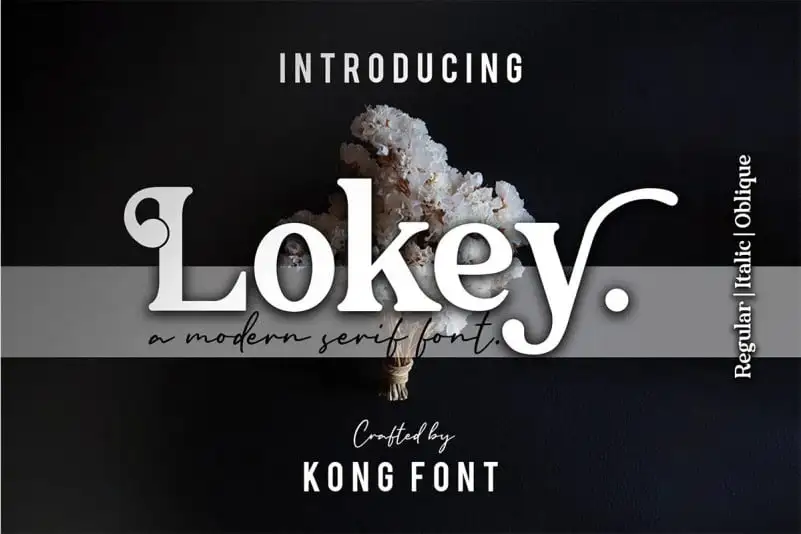
Lokey Serif Font – Download Grátis
A Lokey Serif Font é uma elegante tipografia serifada moderna, criada para quem aprecia sofisticação e destaque visual. Inspirada na moda contemporânea e no design tipo typográfico tradicional, esta fonte traz diversas alternativas de caracteres e ligaturas. Com seu estilo bold e sofisticado, ela é perfeita para criar textos impressionantes em banners, logotipos e publicações de alta qualidade. Seja você um designer gráfico que busca aperfeiçoar seus projetos ou uma editora profissional em busca de um novo recurso tipo, não há dúvidas de que a Lokey Serif será uma escolha inteligente para iluminar seus trabalhos.